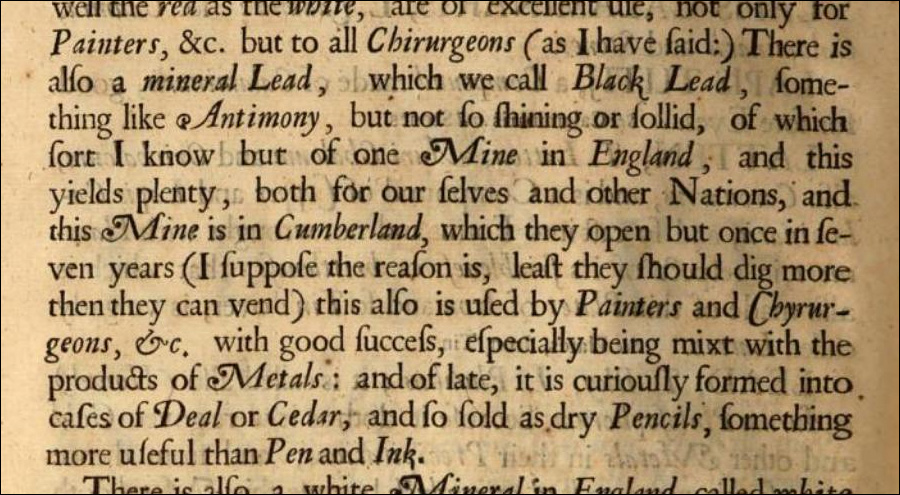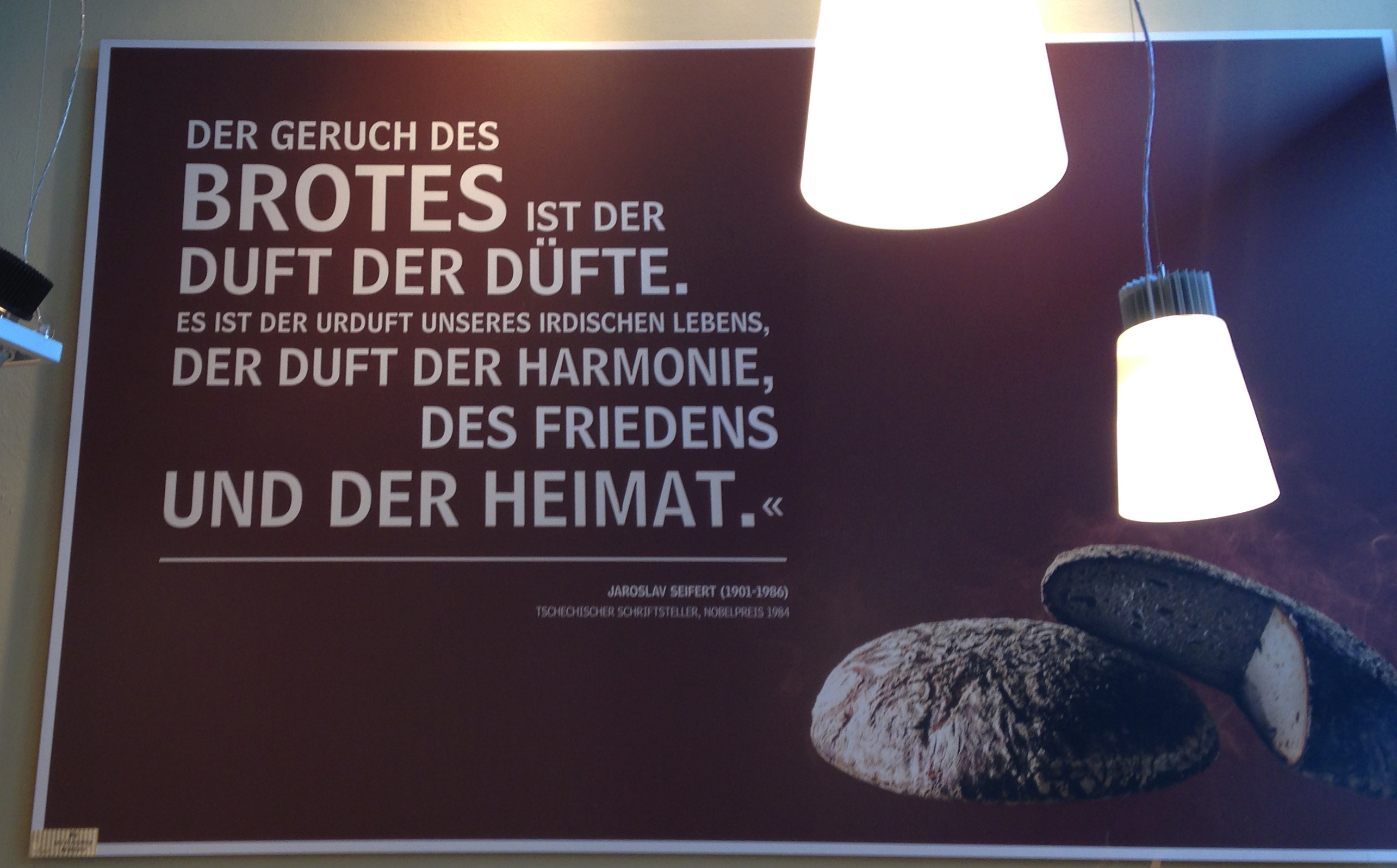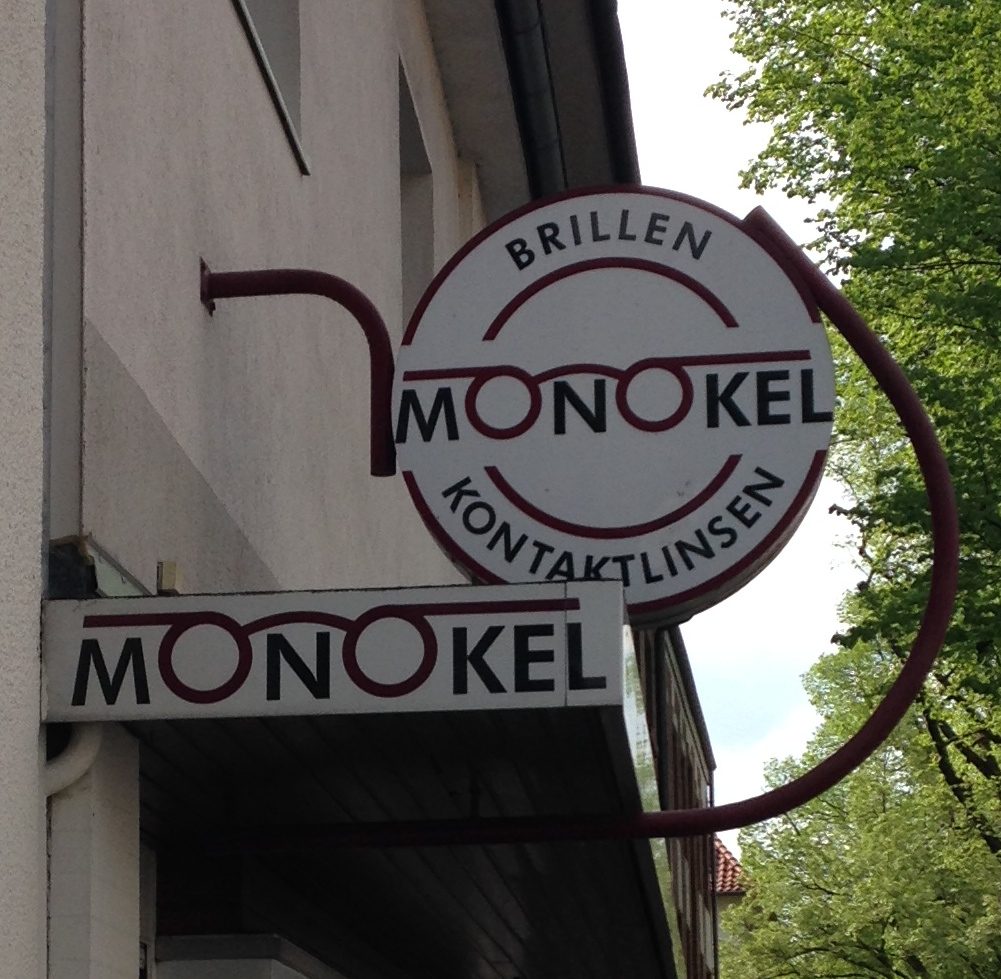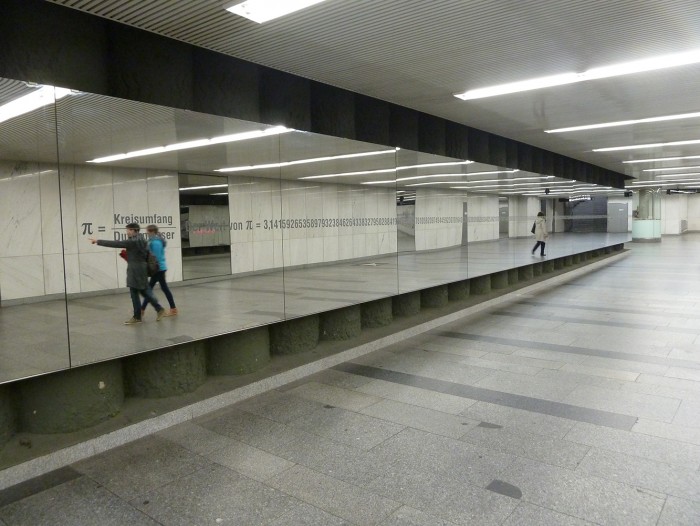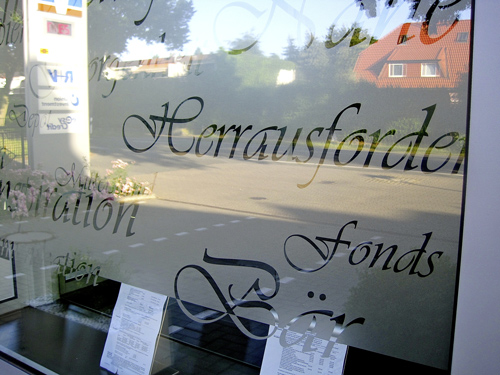
Tatsächlich: Grade in Word ausprobiert, erzeugt auch diese Form. Ist mir noch nie aufgefallen, die Smart-Quote-Funktion habe ich eigentlich immer mit InDesign in Verbindung gebracht. Aber stimmt natürlich, dann hat der Begriff natürlich nichts spezifisch mit InDesign zu tun. Kann aber trotzdem sein, dass ich ihn irgendwo mal gelesen habe.
Das hätte man alles auch ganz anders lösen können:
" ist nur für Anführungsstriche zuständig, und ergibt einfach angeschlagen vor Buchstaben das einfache, doppelt angeschlagen das doppelte öffnende Anführungszeichen, geschieht dies nach Buchstaben oder Ziffern, entstehen so die schließenden.
' ist hingegen für Minuten und Sekunden - bzw Fuß und Zoll zuständig, kommt es einfach oder doppelt angeschlagen direkt hinter Ziffern, sonst bekommt man die geraden Zeichen
und ´´ (also den Akzent doppelt angeschlagen) könnte dann ein schönes Apostroph ausgeben.
So hätte man all die ähnlichen Schriftzeichen bequem auf der Tastatur.
Wenn Inktraps zur Falle werden:
Man beachte insbesondere das R. Leider ist mir das Foto nicht so gut gelungen …
und der Laie möchte auf diesem Möbelstück keinen Staub wischen müssen …
Der technisch versierte Mann holt da den Staubsauger ... ;) Staubtücher fehlen in meinem Haushalt ... ;-)
Natürlich währe es schöner, wenn diese Lettern noch drucken dürften.
Aber anstatt ins Feuerholz zu wandern, wie es leider oft passiert ist, haben sie auf solch einem Tisch, dem man ja noch gut eine Glasplatte verpassen könnte, ein besseres Altenteil.
Würde ich eine Firma aus der Print oder Medienbranche haben, und einen Besprechungstisch suchen, wär das bestimmt keine schlechte Lösung. und die Lettern könnten dann immer noch als Quelle der Inspiration dienen, und von ihrer Geschichte erzählen.
Diese Lade-Animation mit den Schriftzügen ist auch tierisch ätzend. Das könnte man schöner machen ...
Ein paar der Bilder kannte ich schon und irgendwie überzeugen die mich nicht, ohne dass ich konkret sagen könnte wieso?!
Vielleicht weil es relativ eigenschaftslose, nur™ hübsche, nakte Frauen sind, die mit irgendwelchen Mustern bemalt sind und in der Gegend rumstehen. Mir fehlt das Warum oder der Gag der ganzen Sache. Wenn Text und Hintergrund irgendeinen Sinn oder Zusammenhang ergeben würde, könnte ich es eher als gelungene Kunst sehen. So würde ich es zwar nicht Porno nennen aber es ist imo nicht weit vom Pirelli-Kalender entfernt ... :-?
Nacktheit ist für dich also per se Pornografie?
Nein, aber Rule 34 muss ja auch nicht so plakativ, also als »there is porn of it«, formuliert werden, sondern existiert auch in Fassungen wie »sexually related material exists for any conceivable subject«.
Irgendwie blöd, das in Binokel nur ein O ist, ein Monokel dafür aber nur eins gebraucht hätte …
Aus Wien:
Die Zahl geht noch ein ganzes Stück ums Eck … :-)
Leider (mathematisch) schlecht umgesetzt. Der Unterscheidung zwischen »π« und »dem Wert von π« ist hier unnötig und potentiell sogar verwirrend.
π = Kreisumfang / Durchmesser = 3,14…
wäre viel sauberer gewesen.
und an der nächsten Möglichkeit kommt dann
e1671797c52e15f763380b45e841ec32.png = 2,718 281 828 459 045 235 360 287 471 352 662 497 757 247 093 699 95 … und dass dann auch noch ne Ecke weiter.
Nur die Erklärung wird da etwas komplizierter
Sind da evtl. zu viele gegen den Spiegel gedotzt? Greifvogelkulissen für Menschen? ;)
Sichtschutzstreifen an Glastüren und -wänden sind in öffentlichen Gebäuden Vorschrift, da muß nicht erst jemand dagegenlaufen. Ich habe die früher™ mal regelmäßig für eine Bank geklebt.